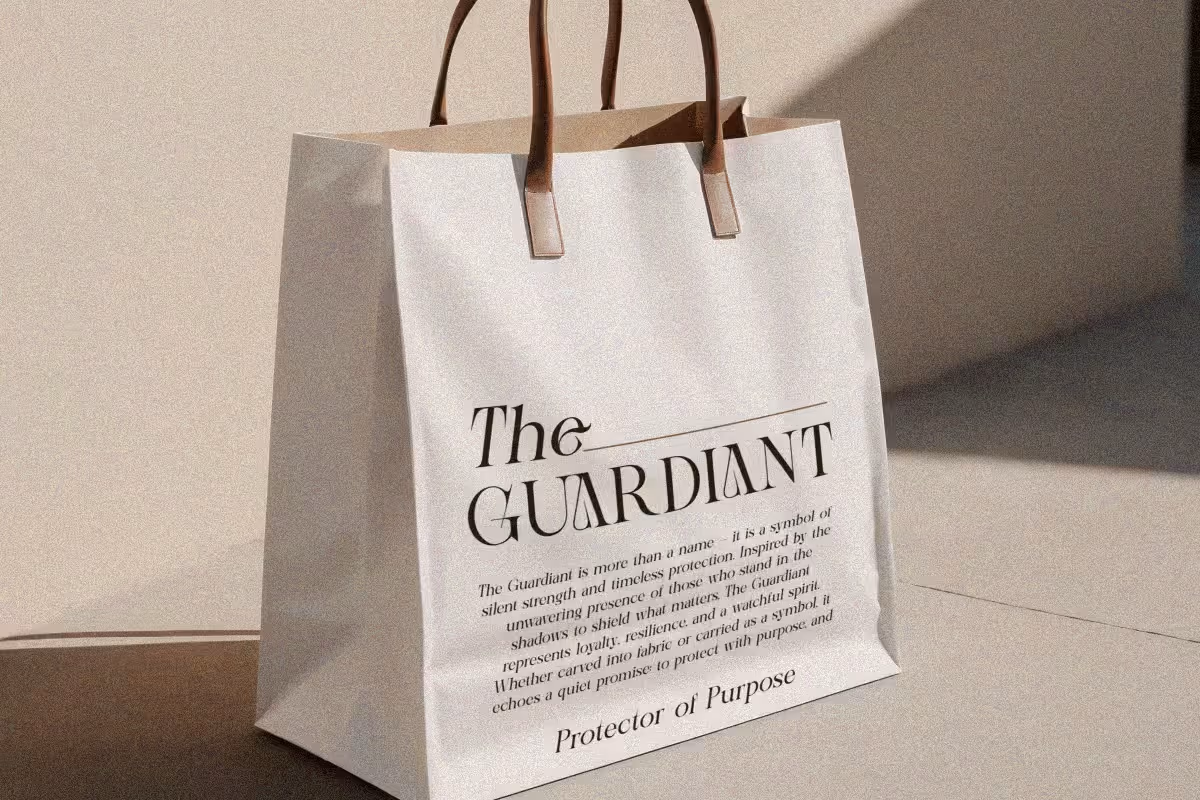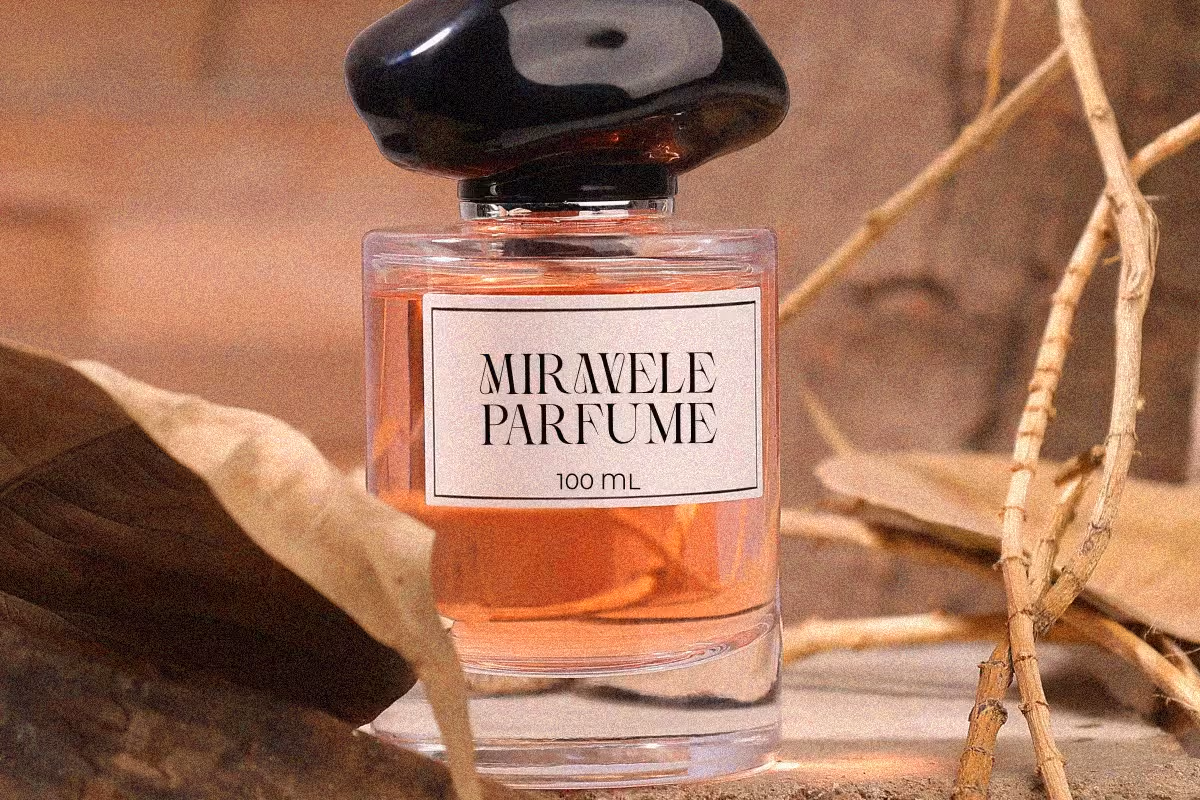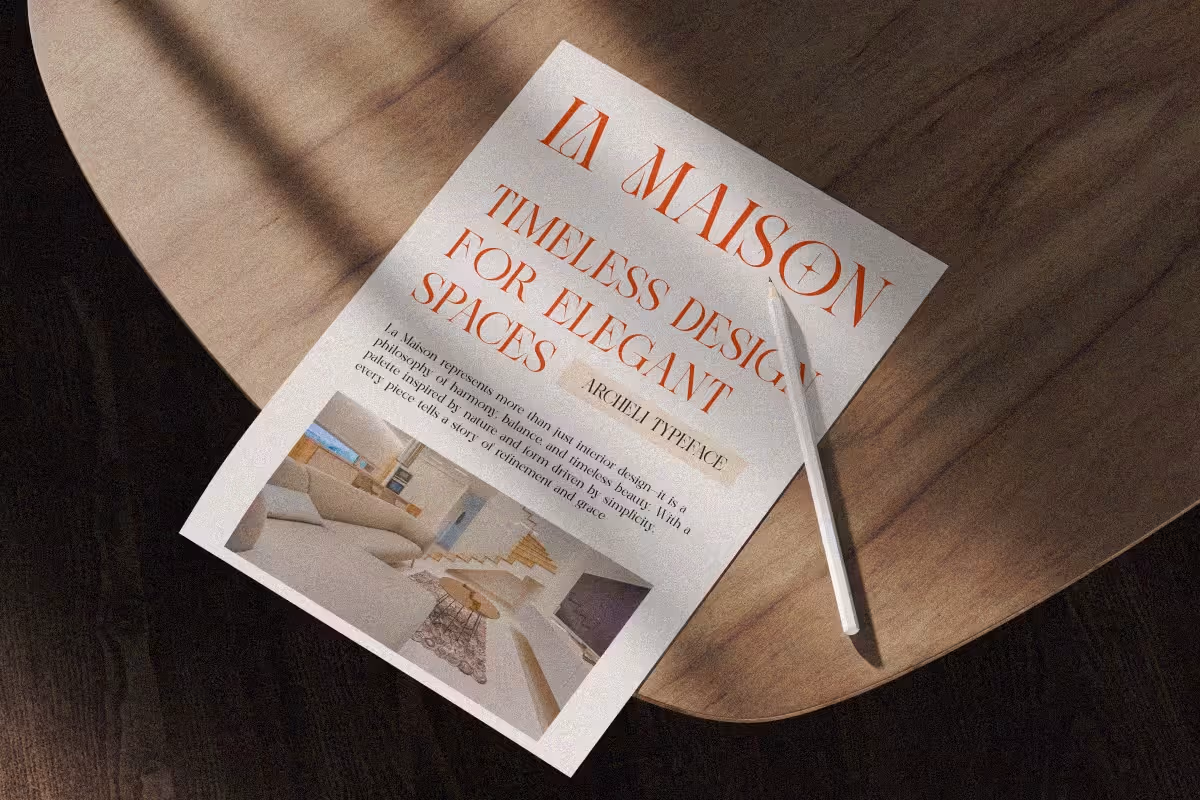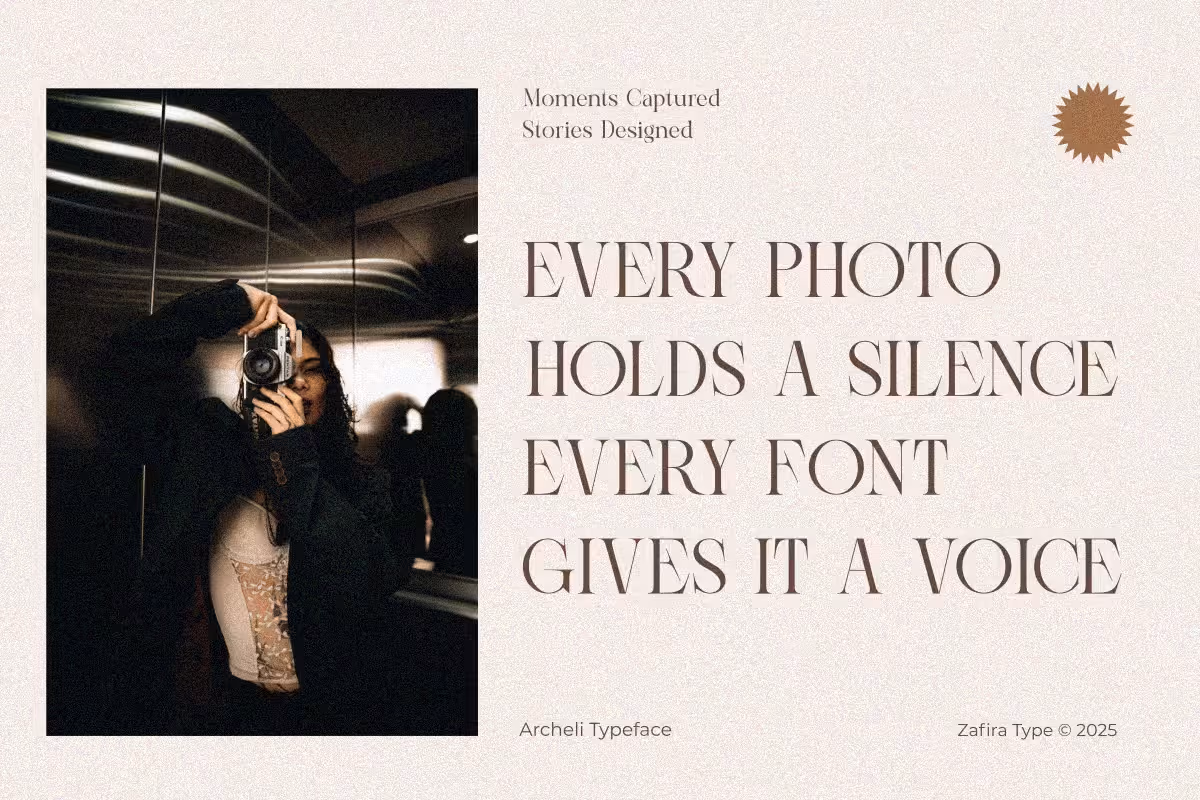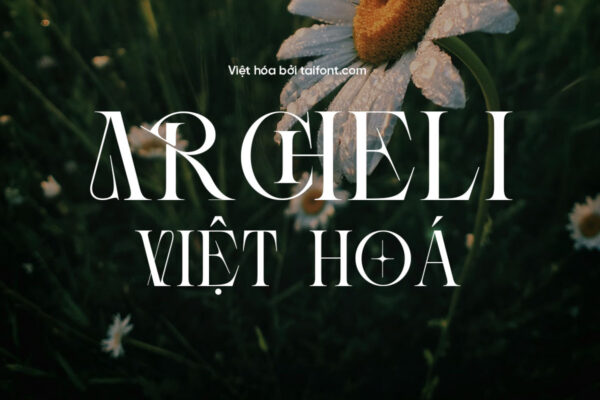
Giới thiệu về Font TF Archeli Việt hóa
TF Archeli Việt hóa là một font chữ có chân (serif) nổi bật với thiết kế đặc sắc, tinh tế và đầy cuốn hút, lý tưởng để tạo nên sự sang trọng và cá tính riêng cho mọi thiết kế. Font này toát lên vẻ đẹp nghệ thuật, hoài niệm nhưng vẫn rất hiện đại, phù hợp để thu hút mọi ánh nhìn và tạo ấn tượng mạnh mẽ.
Với sự tinh xảo trong từng ký tự và tính thẩm mỹ vượt trội, Archeli là lựa chọn hoàn hảo cho các ấn phẩm cần sự sang trọng và khác biệt, đặc biệt là trong các lĩnh vực:
- Thiết kế MV Âm nhạc: Hoàn hảo để sử dụng cho tên ca khúc, tên nghệ sĩ, lời bài hát hiển thị (lyrics) hoặc các thông điệp trong video âm nhạc. Font này giúp tạo phong cách nghệ thuật, độc đáo và lôi cuốn cho MV, nâng tầm trải nghiệm thị giác của người xem.
- Thiết kế tạp chí: Lý tưởng để sử dụng cho các tiêu đề chính, lời dẫn, hoặc nội dung bài viết trong các tạp chí về thời trang, nghệ thuật, âm nhạc, hoặc phong cách sống. Nét chữ có chân đặc sắc của Archeli giúp tăng tính trang trọng và dễ đọc, đồng thời tạo cảm giác cao cấp, thu hút độc giả.
- Thiết kế nhận diện thương hiệu: Phù hợp cho logo, tagline hoặc bộ nhận diện thương hiệu muốn truyền tải sự tinh tế, uy tín và sự thanh lịch. Archeli giúp xây dựng một hình ảnh thương hiệu vững chắc và dễ nhận diện.
Với TF Archeli Việt hóa, bạn có thể dễ dàng thổi hồn tinh tế, sang trọng và vẻ đẹp hoàn hảo vào các thiết kế, tạo ra những sản phẩm không chỉ đẹp mắt mà còn đầy cảm xúc và sức hút đặc biệt.